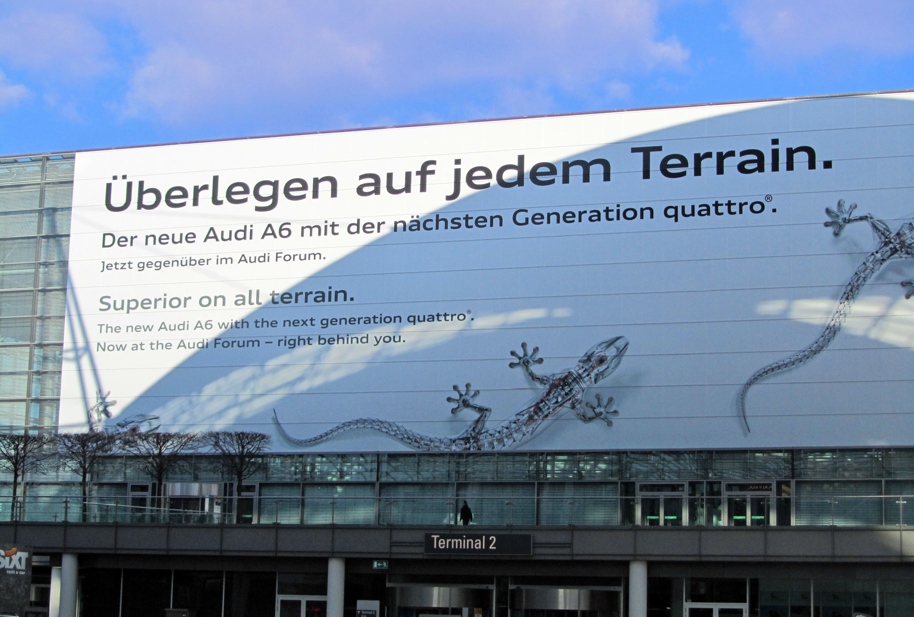
Suche ähnliche Schriftart zur AudiType
ich bin auf der Suche nach einer ähnlichen Schrift zur Audi-Schrift im digitalen Bereich – genauer gesagt zu der Schriftart, die Audi in Softwareprodukten wie im Virtual Cockpit verwendet. Leider konnte mir WhatTheFont keine zufriedenstellende Alternative generieren. Im Genauen suche ich eine ähnliche Schrift wie jene, die in diesem Interface verwendet wird: http://www.audi.de/content/dam/vorsprung_durch_technik/Bilder/2014/03/Audi%20virtual%20cockpit/Gallery_02.jpg
Kann mir jemand helfen?
Audi verwendet auch auf den Displays die Hausschrift. Siehe hier.
Super, danke für eure Antworten! Auf den Link von Audi bin ich auch schon gestoßen ;-) Allerdings scheint das eine alte Schrift zu sein. Jedenfalls wurde diese Schrift nicht im aktuellen Virtual Cockpit verwendet.
Die Allumi finde ich schon ziemlich nah dran. Ich glaube eine viel ähnlichere werde ich nicht finden… :-(
Oh super cool! Danke!! Hab mich mal durch einige durchprobiert. Allerdings kommt's mit den Ziffern nicht immer ganz so hin. Die AudiType drückt die gewünschte Sportlichkeit schon noch ein wenig besser aus…Mich stören bei den Alternativen oft die "1" und die "3". Wenn man sich das Virtual Cockpit nochmal ansieht, kommt das halt schon anders…Die beste Typo fand ich bisher die Allumi… :-)